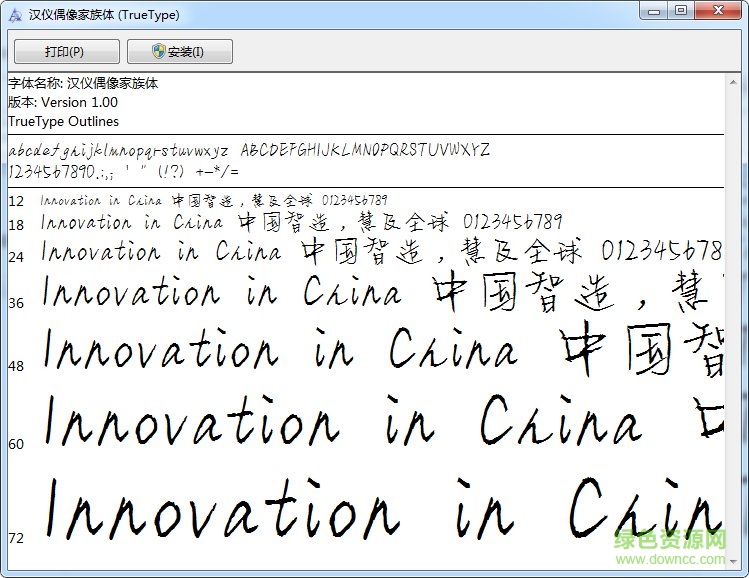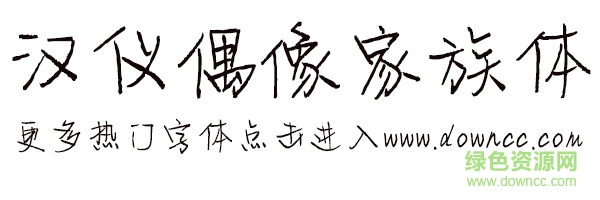
漢儀偶像家族體字體ttf版可以在windowns和mac系統(tǒng)上安裝使用。這款字體線條筆直有力,有點(diǎn)像鋼筆字體。多用來設(shè)計(jì)一些廣告牌使用!歡迎網(wǎng)友們前來綠色資源網(wǎng)下載安裝。
漢儀偶像家族體字體是一款全新收集的偶像家族的字體,該字體的視覺效果非常好,因此在多個(gè)行業(yè)領(lǐng)域被廣泛使用!